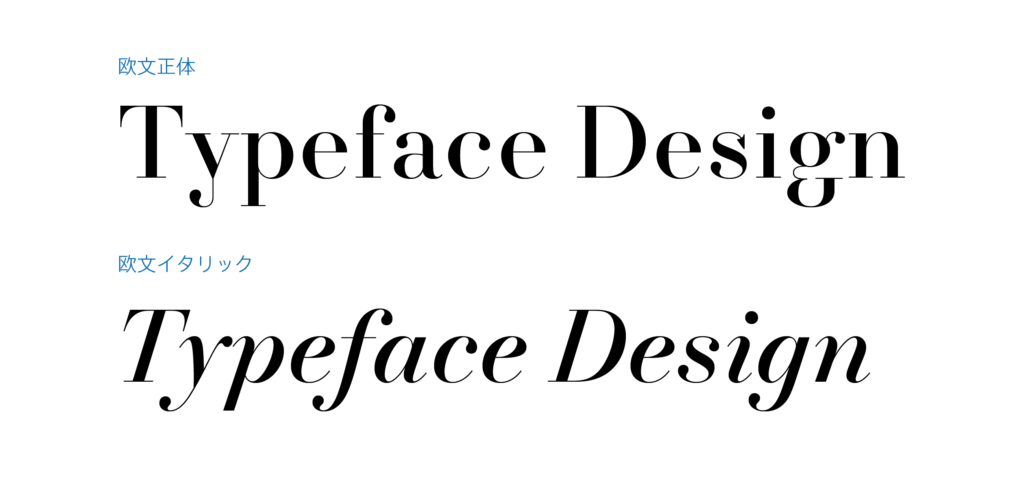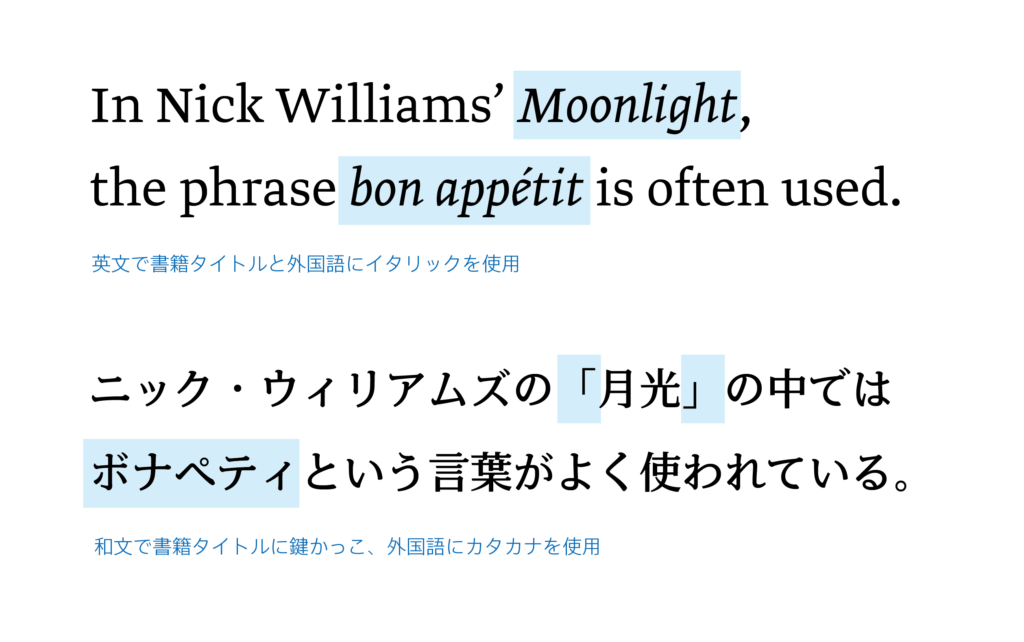
欧文イタリック01「イタリック」
タイププロジェクトでは2020年に濱明朝イタリックをリリースしました。
イタリックは日本ではあまり馴染みがない書体スタイルですが、英語などラテンアルファベットを使用するいくつかの言語圏では書籍や辞書などに頻繁に登場します。
日本語の文章の中でよく見られるラテンアルファベットのスタイルは、正体(アップライト)と呼ばれる文字がまっすぐなものです。それに対してイタリックは文字が右向きに傾斜した斜体です。
英語圏などの書籍でも本文には正体がメインで使用されますが、本文中の書籍や作品のタイトル・外国語・登場人物の台詞の表記などにイタリックが使用され、文章内の情報を区別する役割を果たします。日本語で外来語にカタカナ、タイトルや台詞にはカギかっこ等を使用するのと同様です。
その他にもイタリックのもつ有機的で華やかなデザインを生かし、単体で装飾的な要素として使用されることもあります。